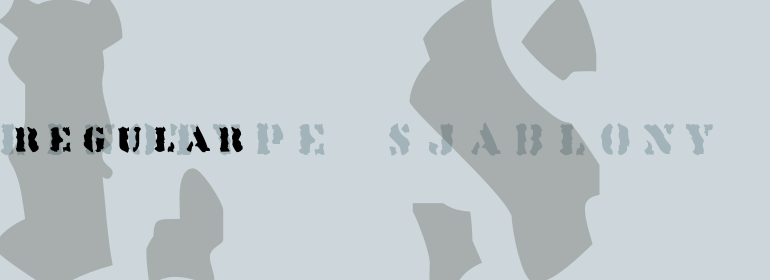
Linotype Sjablony™
Linotype Sjablony™,这款字体结构工整、笔画清晰,兼顾美观与易读性,适用于标题、正文、海报、包装、LOGO 等多种场景。字形优雅稳定,风格百搭耐看,适配日常排版与创意设计,让文字呈现更舒适、更具质感。Linotype Sjablony™一笔一画,皆是细节,以均衡的比例、流畅的线条打造舒适视觉体验,字形端正大气,风格简约现代。无论是商业设计、品牌宣传还是日常排版,都能轻松驾驭,让文字更有格调与力量。Linotype Sjablony™字体下载。